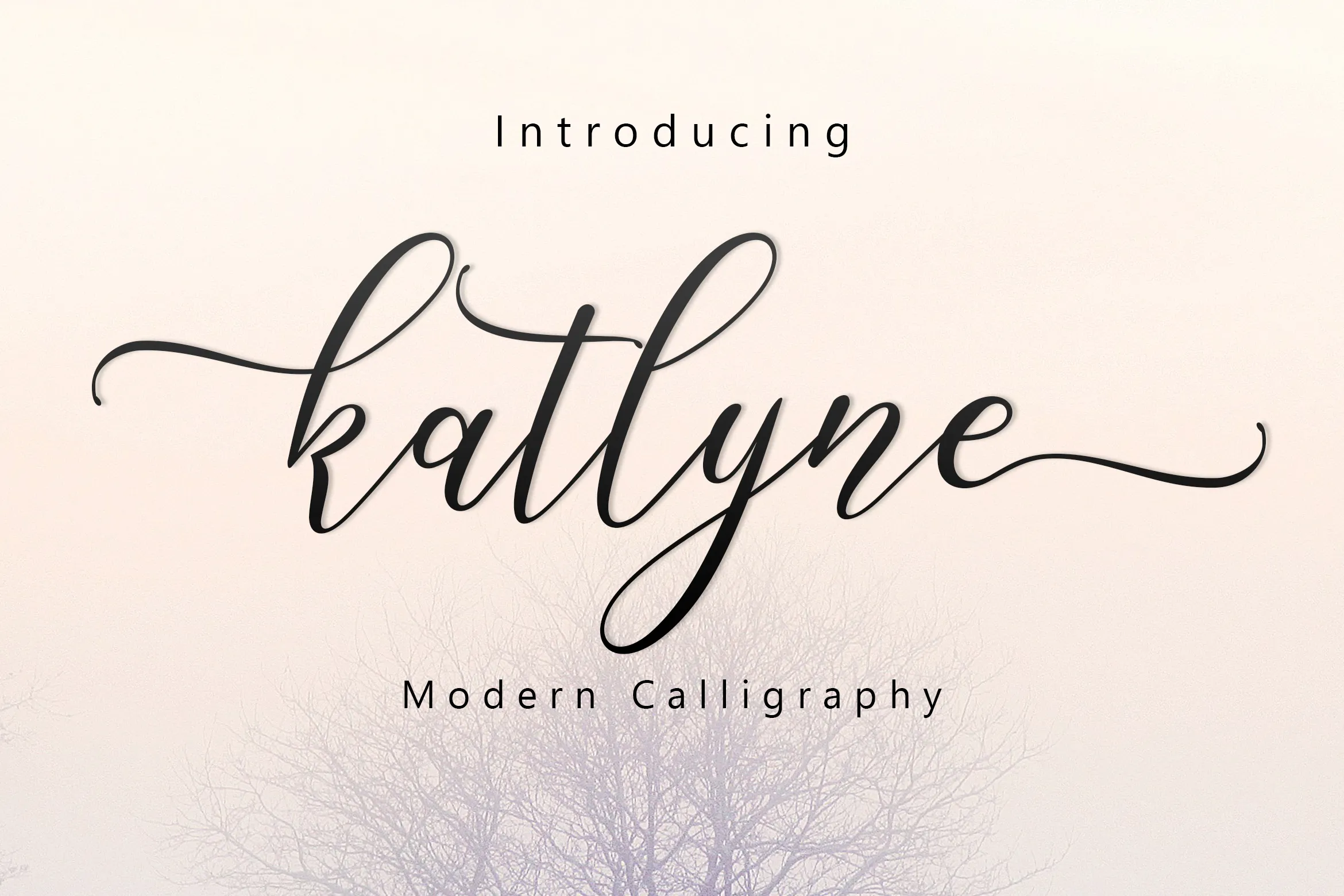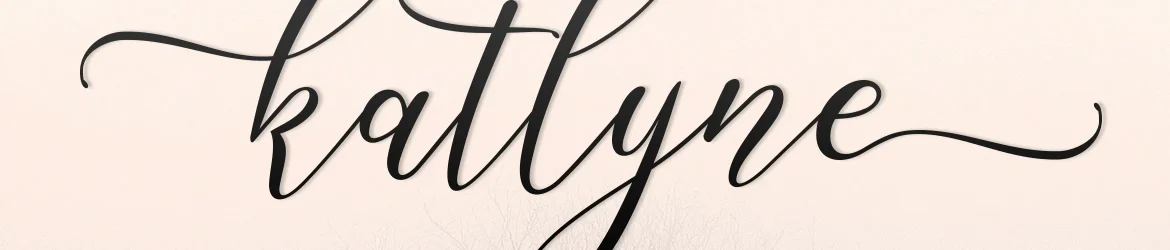
A fonte Katlyne Script é uma chamada moderna e fashionável criada pela designer C00zona. Ela oferece um toque leve e engraçado que faz do Katlyne algo especial para seu projeto gráfico. Com seus caracteres adoráveis e linha de fundo levemente ondulante, esta fonte traz uma sensação de conforto visual que é extremamente agradável aos olhos. Katlyne Script vem equipada com 250+ caracteres, permitindo ao designer explorar amplas possibilidades na criação de textos. Além disso, os designers podem explorar ainda mais os recursos abertos e alternativos através da introdução de feições como Swash, Set Estilístico, Alternativas Estilísticas, e Alternativas Contextuais. Esses recursos adicionais permitem que o designer adicione uma profundidade a seu design. Katlyne Script é perfeita para qualquer aplicação onde um ar jovial e moderno seja desejado. Seja em gráficos de marca, publicações online ou até mesmo em design de ilustração, Katlyne proporciona um toque único que certamente destacará seus trabalhos.